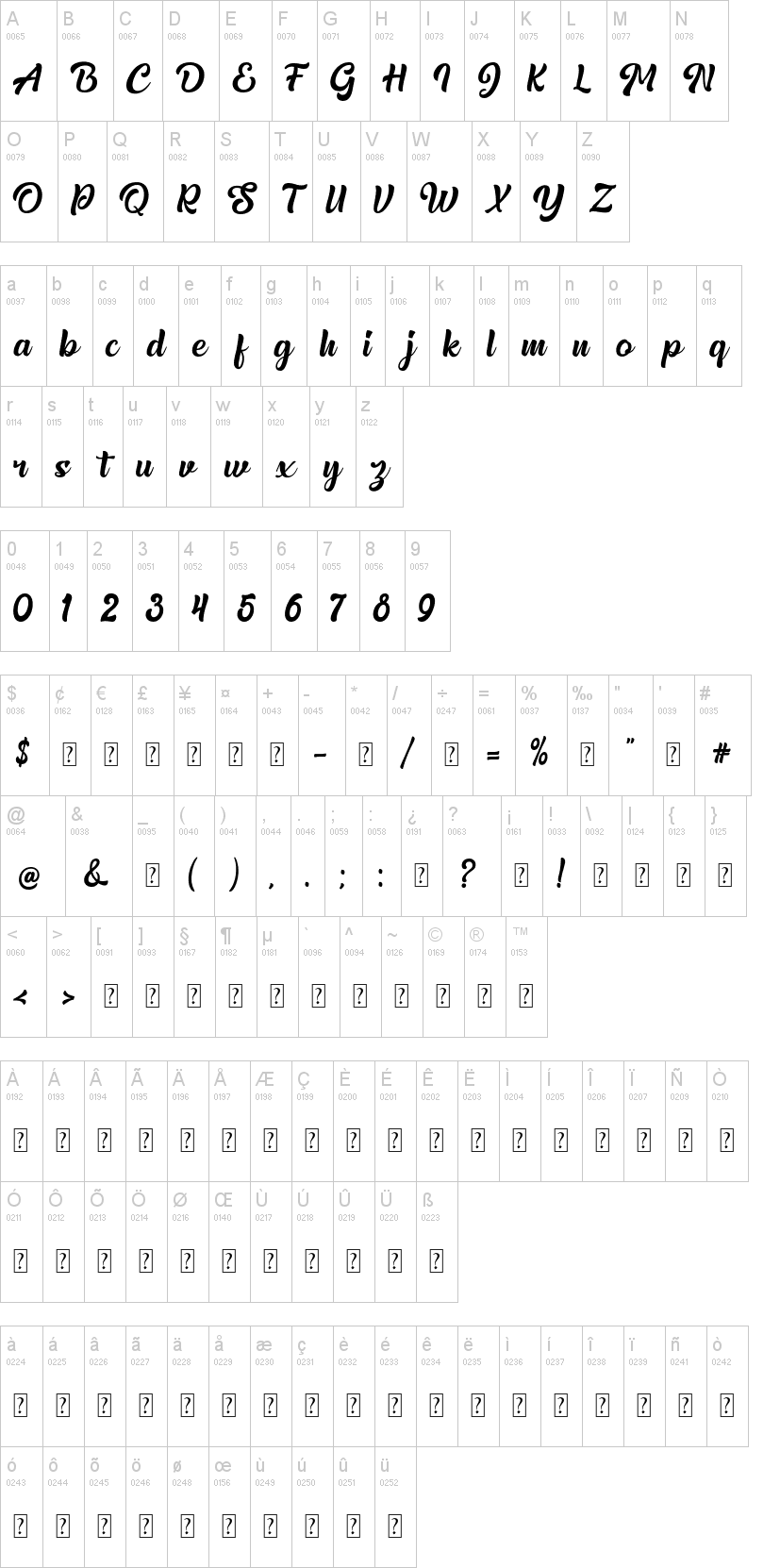
Realistica 字体是一款由西班牙设计师Javier Quintana设计的扩展型英文字体。它的设计灵感来自于现代文本排版与平面设计,主要用于标题、标识、标签、标题和封面等。它具有简洁、明快、精致、清新的特点,可以为设计师提供更多的创意空间。Realistica 字体具有超大的字形和较大的行距,可以让文本看起来更加明亮、简洁、精致。它的字形设计精良,拥有良好的可读性,可以满足多种不同类型的文本应用,如标题、标识、标签、标题和封面等。它可以帮助设计师快速创建出精致、清新、简洁的设计效果。内容介绍
Realistica是一款非常不错的手写艺术字体,具有很好的视觉感,适合于文化类的宣传设计、商业类品牌的广告和产品包装设计以及个性化文字排版等较多场景。